適合各種場合的 15 種免費書法字體
已發表: 2019-09-15您是否正在尋找一種獨特的字體來添加到您的設計中? 書法字體可能正是您所需要的。 在線提供大量免費書法字體,您可以輕鬆地為您的項目添加一些額外的東西。 書法字體有許多不同的風格,從整潔到超級裝飾。 在這篇文章中,我們整理了一系列免費書法字體,您可以立即下載。
某些書法字體具有 Open Type 功能,可提供不同的色板和字母樣式。 這些字體只有在有 Webfont 版本時才能在網站上使用。 您將需要一些最少的 CSS 技巧來訪問 Open Type 功能。 對於看起來有點複雜的字體,只需聯繫設計人員,了解其 Open Type 設計的特定 Webfont 用法。
1. 偉大的共鳴
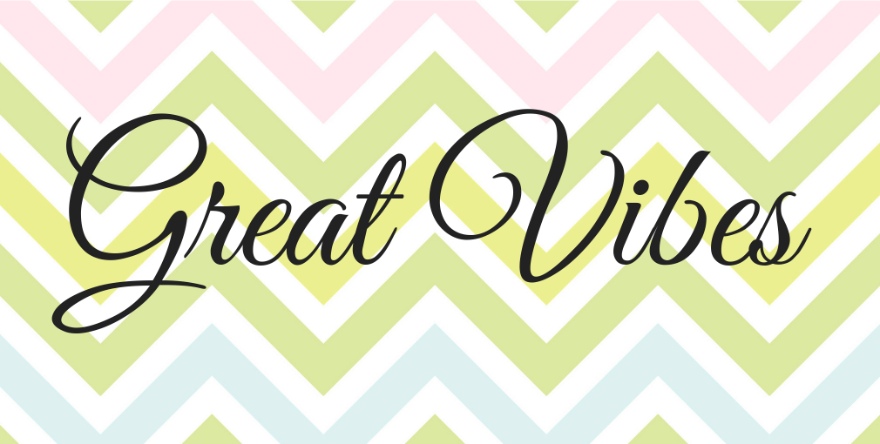
在書法字體方面,Great Vibes 是歷來最受歡迎的字體之一。 使用大寫字母和均勻基線很容易閱讀。 字母連接乾淨,上升和下降是循環的。 這種字體非常適合較大的標題和副標題,與 Roboto 和 Open Sans 等簡單的 sans 字體搭配看起來很棒。 Great Vibes 可免費用於個人和商業用途,並且還有 Google Webfonts 版本。
2. 亞利桑那州
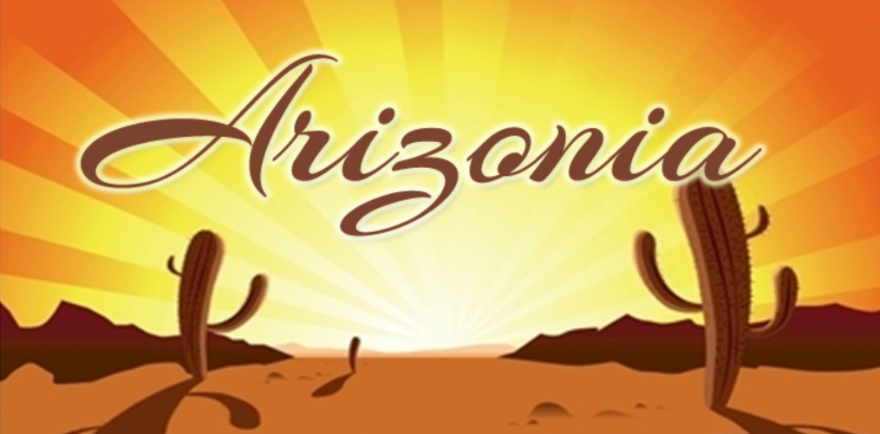
Arizonia 是一種現代書法字體,帶有微妙的阿拉伯風格。 它的靈感來自標誌畫家的駱駝毛刷創作的字母。 上劃很細而下劃很重,創造了很好的平衡。 向右的小角度賦予字體個性。 這種字體非常適合較大的標題和引號。 將它與 Josefin Sans 或 Merriweather 搭配使用,以獲得有趣和通風的設計。 該字體帶有免費的個人和商業許可證,位於 Google Webfonts 目錄中。
3. 謝潑德夫人
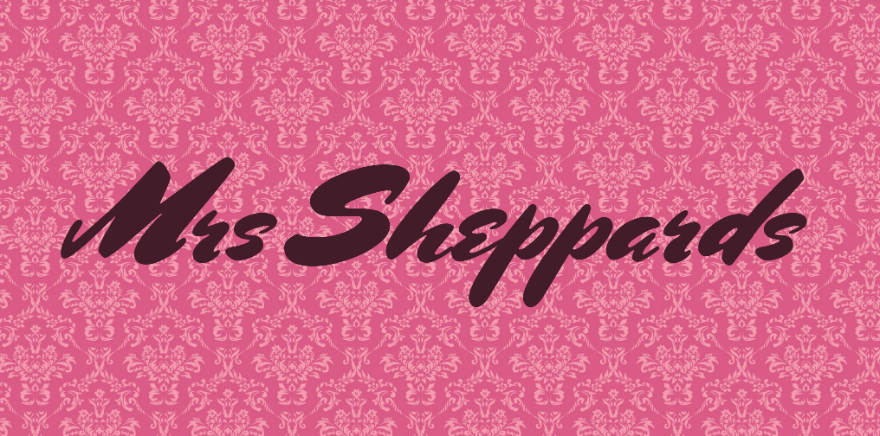
Thw Sheppards 書法字體是 Charles Bleumlein Script 系列的一部分。 這是從 1930 年代和 1950 年代之間原始手工創建的腳本字體以數字方式重新創建的字體集合。 這些字體是使用真實人物的簽名創建的,並以虛構的名字命名,以保持這種簽名精神的活力。 這種字體具有有趣的粗筆劃,使其比該系列中的其他字體更具現代感。 使用 Mrs Sheppards 字體作為標題或菜單標題,並將其與 Lato 或 Montserrat 配對以獲得乾淨的設計。 該字體帶有免費的個人和商業許可證,以及 Google a Webfonts 版本。
4. 露西
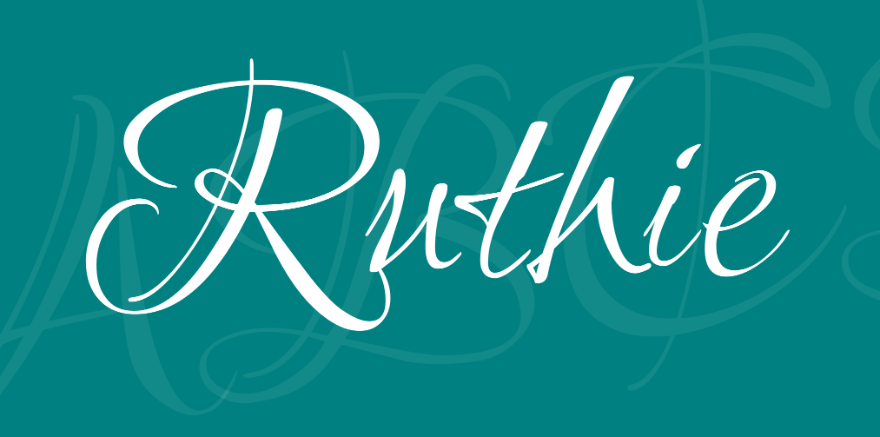
Ruthie 是一種具有個人風格的書法字體。 這些字母沒有聯繫,而是有自己的個性。 大寫字母具有裝飾風格,末端有短漩渦。 字母 i 上的點看起來像一個傾斜的水滴或蠟燭火焰。 這是一種獨特的書法字體,具有很大的潛力。 Ruthie 擁有免費和商業用途的免費許可以及 Google Webfonts 版本。
5. Endestry
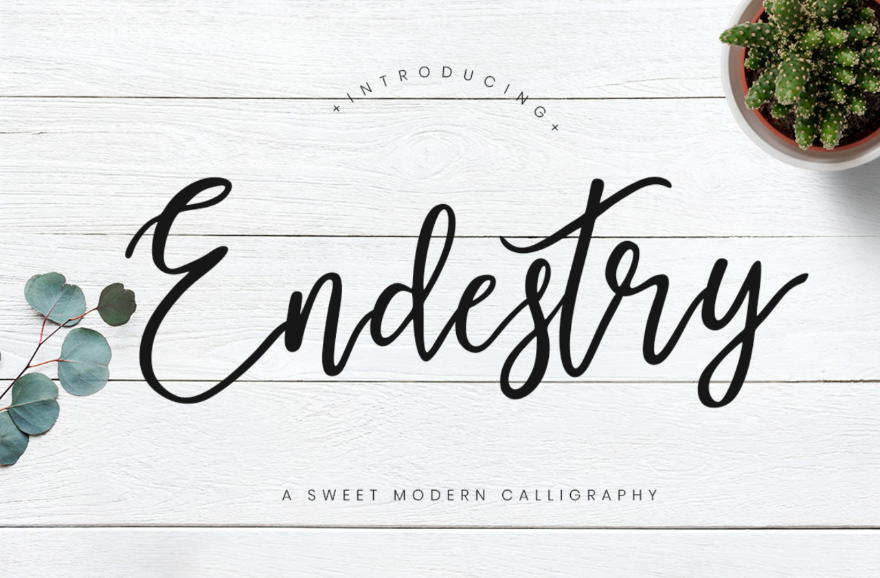
Endestry 是一種外觀清新的現代書法字體。 它類似於 Instagram 和女性網站上最喜歡的字體。 這種字體有華麗的循環和獨特的字母連接器。 將它與像 Montserrat 或 Raleway 這樣的全大寫簡單字體配對,它在任何創意項目中都會看起來很棒。 Endestry 可免費用於個人和商業用途,並在下載文件夾中包含一個 .woff (Webfont) 文件。
6. 沙梅拉
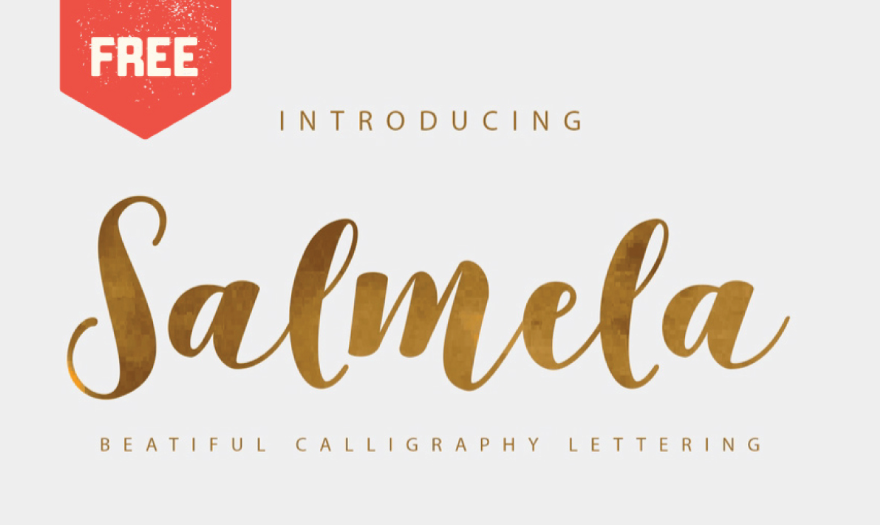
Salmela 是一種漂亮而有趣的書法字體,具有不均勻的基線。 這種字體本身和大字體看起來都很棒。 它非常適合大標題甚至徽標。 Salmela 即將成為一種女性化字體,但由於其粗筆劃,也可用於更性別平等的設計。 此字體可免費用於個人和商業用途,但沒有 Webfont 文件。 要在 WordPress 中使用此字體,您需要將其轉換為 .woff 或使用 Use Any Font 插件。
7. 女王
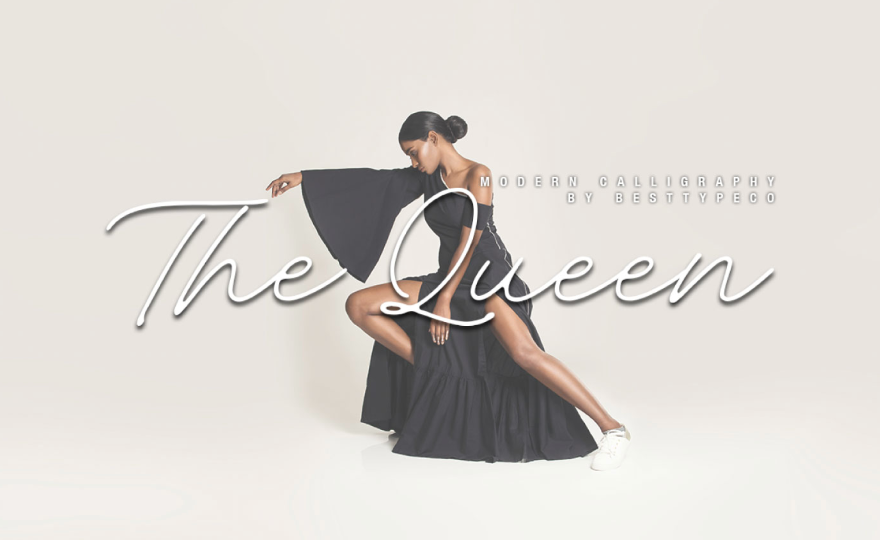
女王是一種精緻的現代書法字體,非常適合許多項目風格。 像這樣的免費書法字體特別通用,因為它們適用於標題和塊文本,如引號或推薦。 這種字體可以為原本極簡主義或標準的設計賦予個性化的外觀。 Queen 可免費用於個人和商業用途,並通過 Webfont 下載。 這種字體已準備好用於您的網頁設計項目。
8.悉尼
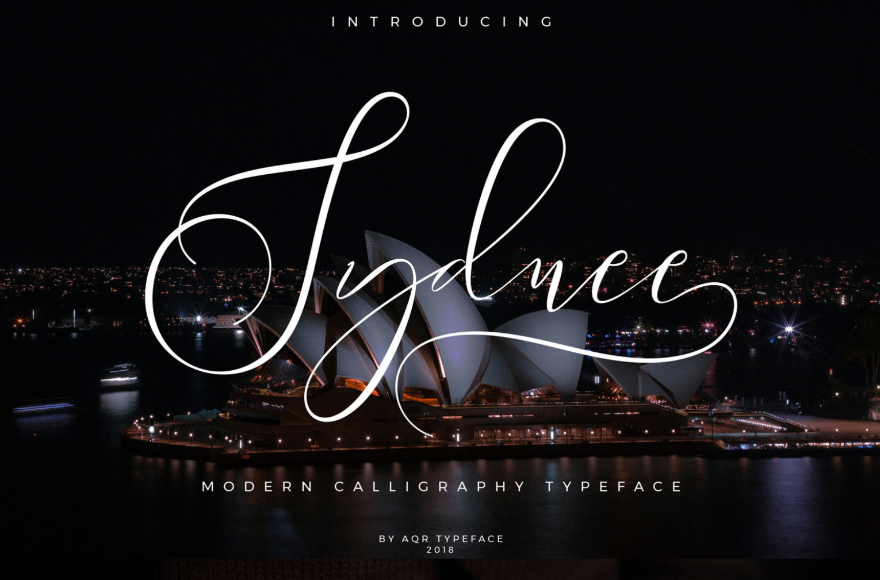
Sydnee 是一種優雅的書法字體,帶有華麗的循環和花飾。 演示字體可免費用於個人和商業用途。 免費版本只有一個 .otf 文件,因此您需要使用該插件才能使其工作。 完整的付費版本確實帶有 Webfont 和許多不同的花體和連字樣式。 這是一種漂亮的風格化字體,適用於與婚禮相關的網站和女性化設計。
9. 漢斯頓
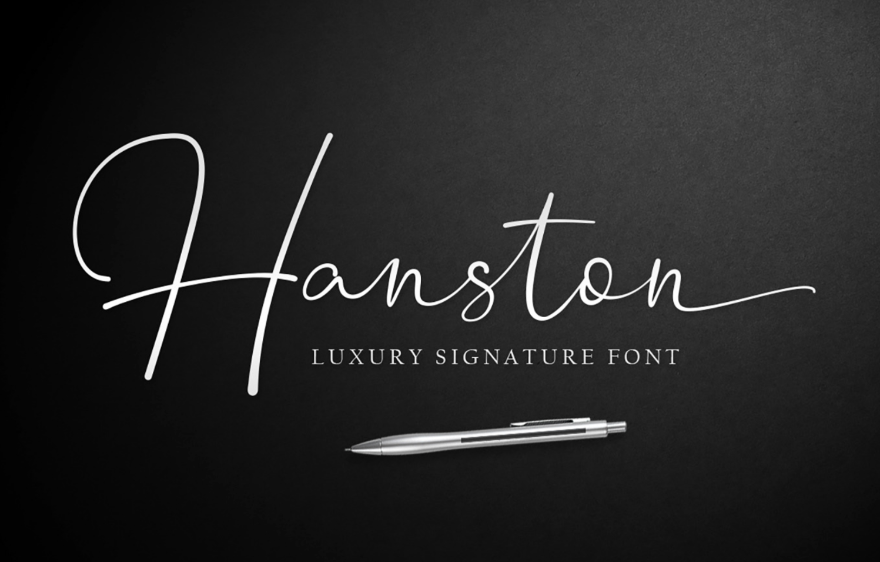
Hanston 是一種優雅奢華的書法字體。 它簡單而經典的風格適用於許多不同類型的設計。 大寫字母偏大,而小寫字母則偏小。 這種尺寸差異在兩者之間創造了一種華麗的平衡。 此字體僅供個人免費使用。 如果您想將其用於商業用途,則需要購買許可證。 商業許可證帶有 Webfont 版本。
10.美麗的心
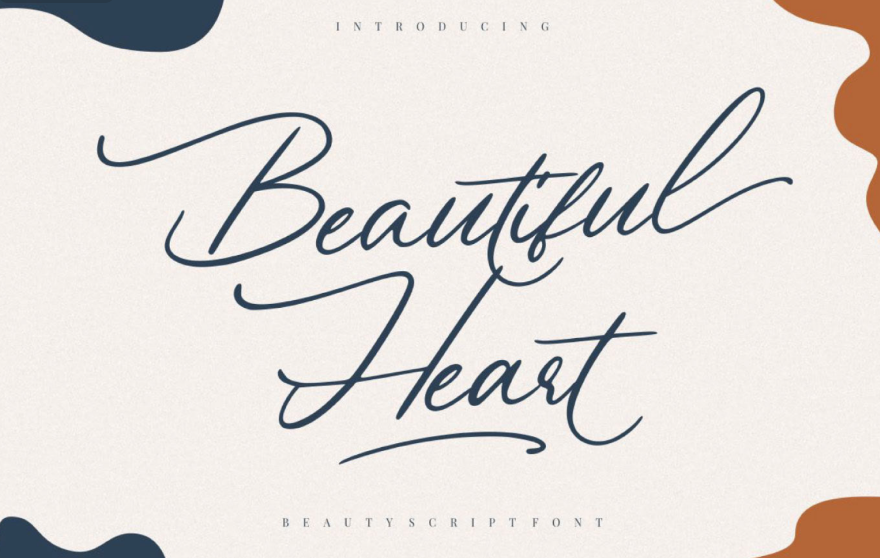
Beautiful Heart 是一種輕鬆活潑的書法字體。 筆劃粗細相近,環圈傾斜。 這是一種偉大的字體,用於大字母的裝飾目的。 具有大寫字母和小寫字母的字體風格,這是現代優雅設計的華麗字體。 這種書法字體僅供個人免費使用,並帶有 .otf 文件。 需要購買商業許可證並且包含 Webfont 版本。
11. 輕鬆十一月
Easy November 是一種漩渦字體,具有獨特的字母形狀和样式。 每個字母的循環都不同,基線不均勻。 對於需要一點額外個性的創意設計來說,這是一種有趣的字體。 這種字體可供個人免費使用,並且可以從設計師的網站上購買許可證。 沒有現成的 Webfont,因此您需要生成它或使用上面提到的插件。
12. 比泰
Bitthai 是一種華麗的薄型書法字體。 它非常適合優雅和女性化的設計。 循環很大,元音很小,因此創造了一種有趣且視覺上豐富的平衡。 這是一款僅供個人使用的免費演示字體。 完整的許可細節在設計師的創意市場銷售頁面。 不幸的是,它沒有 Webfont 版本,但可以使用我上面提到的插件輕鬆添加。 確保您擁有桌面許可證,可以在您獲得報酬的設計中使用該字體。
13. Chandrawinata
Chandrawinata 是一種休閒書法字體,有兩種風格; 正常和斜體。 這種字體時尚而有趣,帶有獨特的字母連接器,使單詞看起來輕鬆和拉伸。 免費許可證僅供個人使用,包含所有標準字體文件,包括 .woff。 免費版本不是演示字體,它實際上是整個字體設計。 商業許可證可通過 Fontbundles 獲得。
14. 布里約
Brillyo 是一種有趣且現代的書法字體,帶有可愛的色板。 這是一種年輕而充滿活力的字體,在千禧年風格的設計中看起來很棒。 免費版本僅供個人使用,商業許可可通過 Fontbundles 獲得。 完整的商業字體包括 Webfont 版本。 此外,這種字體中的 Open Type 樣式可以通過一些 CSS 訪問,但只能通過商業許可進行訪問。
15. 德西安蒂
Desyanti 是一款適用於 Instagram 的字體,適用於任何女性化設計。 橫線細而精緻,與字母的粗大筆劃相得益彰。 基線有跳舞的設計,使字體俏皮且充滿活力。 這種免費的書法字體僅作為個人使用的演示提供。 對於商業用途,您將需要許可證。 此字體沒有 Webfont 版本,但您可以使用 Use Any Font 插件在沒有 Open Type 功能的情況下使用它。
結論
您是否嘗試過在您的設計中使用書法風格的字體? 如您所見,它們可以為任何項目添加視覺豐富度。 此外,每種字體都有自己獨特的風格,而其他字體則具有相似的外觀。 借助 Webfont generation、像 Use Any Font 這樣的多功能插件以及在某些情況下的一些 CSS,可以在您的網頁設計中使用這些字體中的任何一種。